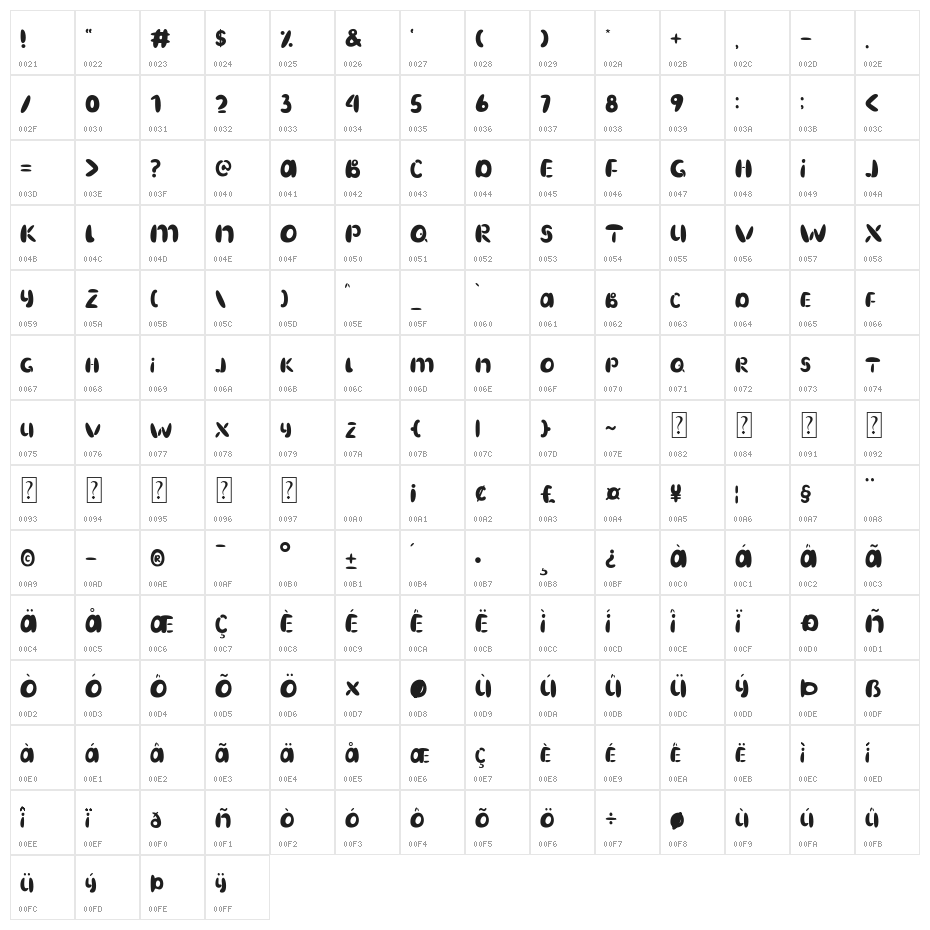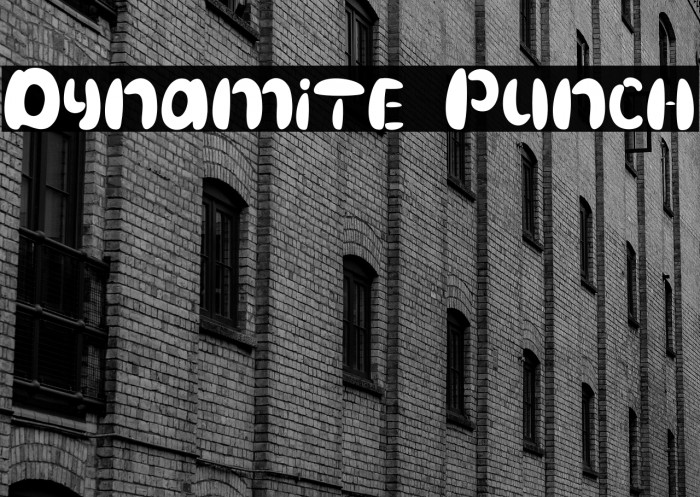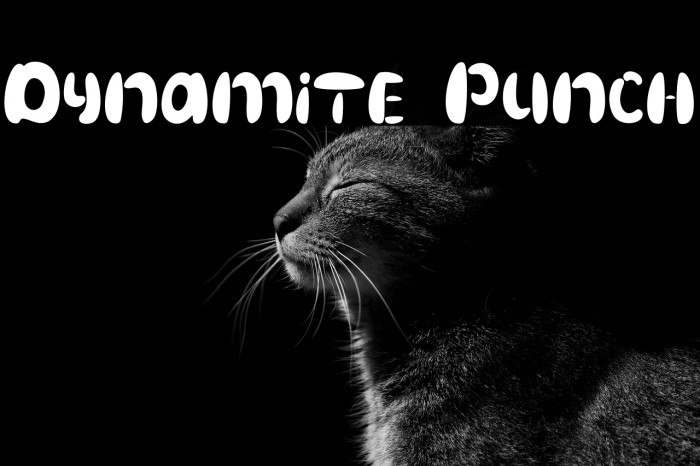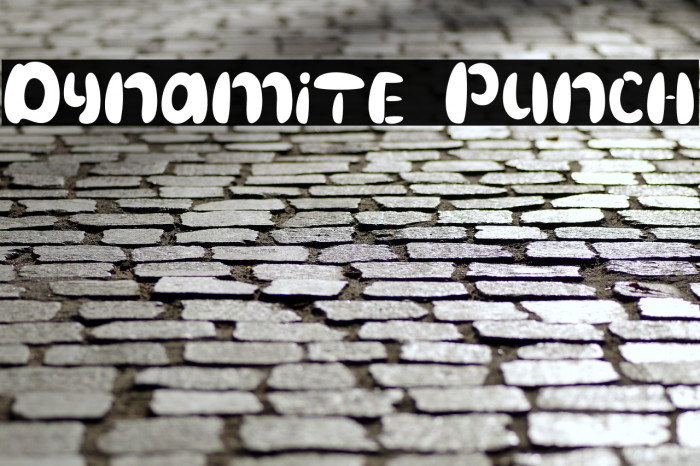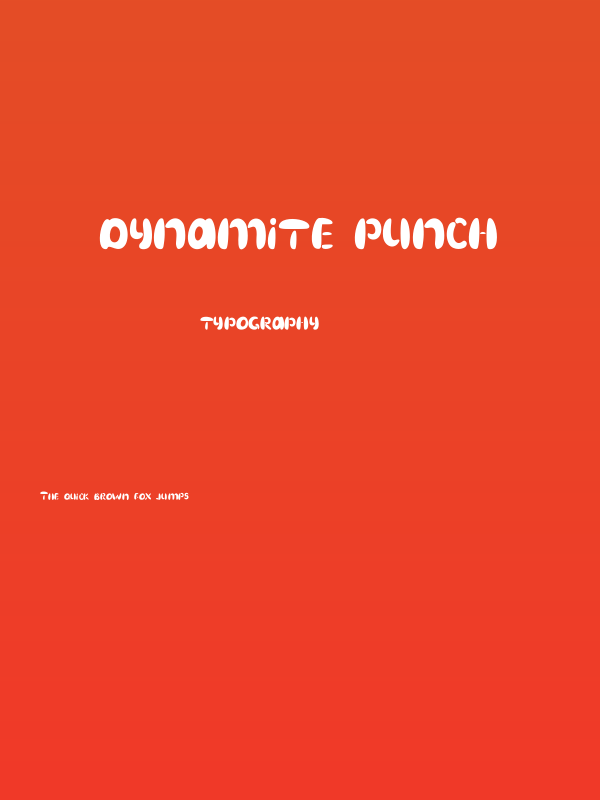
Dynamite Punch Font
| Stil general | Playful, Retro |
| Proiecte propuse | Perfect for children's books, comic strips, playful branding, and event posters. |